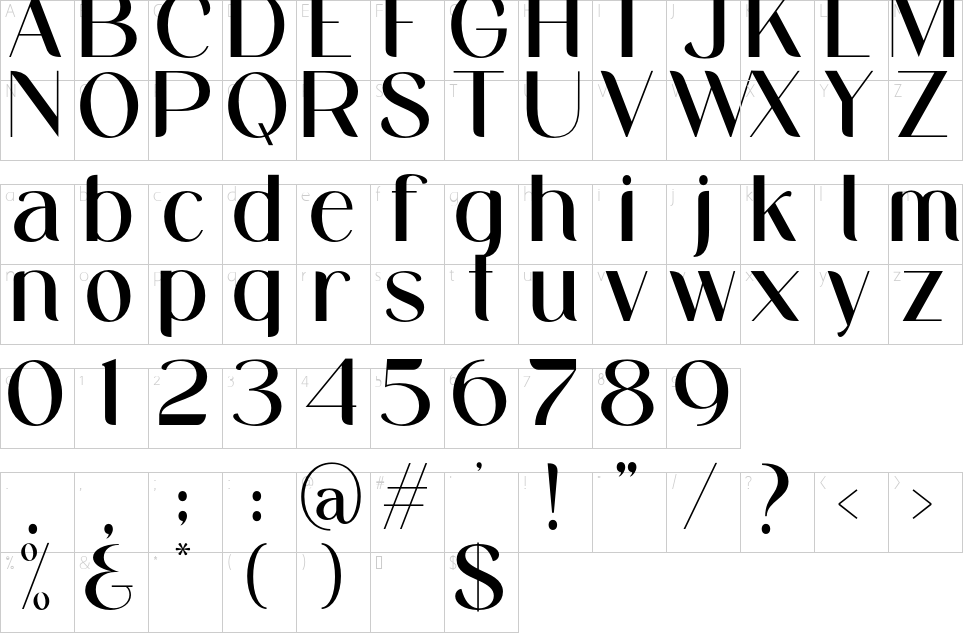
A fonte Midland oferece uma experiência visual agradável e elegante, perfeita para estilos gráficos que valorizam uma paleta de cores suave e linhas retas. Desenvolvida pela Areatype, esta fonte é uma ótima escolha para designers que buscam um equilíbrio perfeito entre simplicidade e modernidade. Midland foi projetada para complementar diversos tipos de trabalho, desde editoriais até logos e marcas, proporcionando uma estética limpa e sofisticada. Com um download de mais de 1.935 vezes, é claro que designers e profissionais de gráfica estão valorizando a versatilidade e a facilidade de uso desta fonte. Para quem busca uma paleta de opções de fontes gratuitas, Midland é uma excelente escolha para estabelecer um design impecável e moderno.